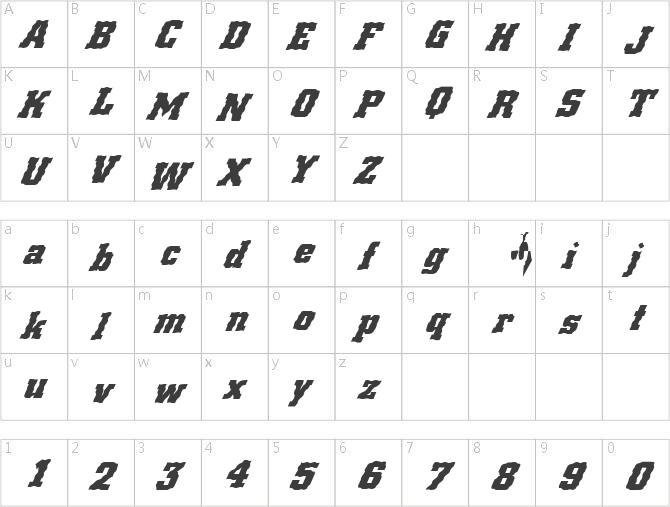
FZ BASIC 53 WAVEY ITALIC
FZ BASIC 53 WAVEY ITALIC介紹
FZ BASIC 53 WAVEY ITALIC字體字庫是一款讓人賞心悅目、百看不厭的英文字體,適合各類廣告和產品包裝設計應用,字體大小0.11MB,格式為ttf字體,上傳用戶是Who am I?,作者/版權方為未知